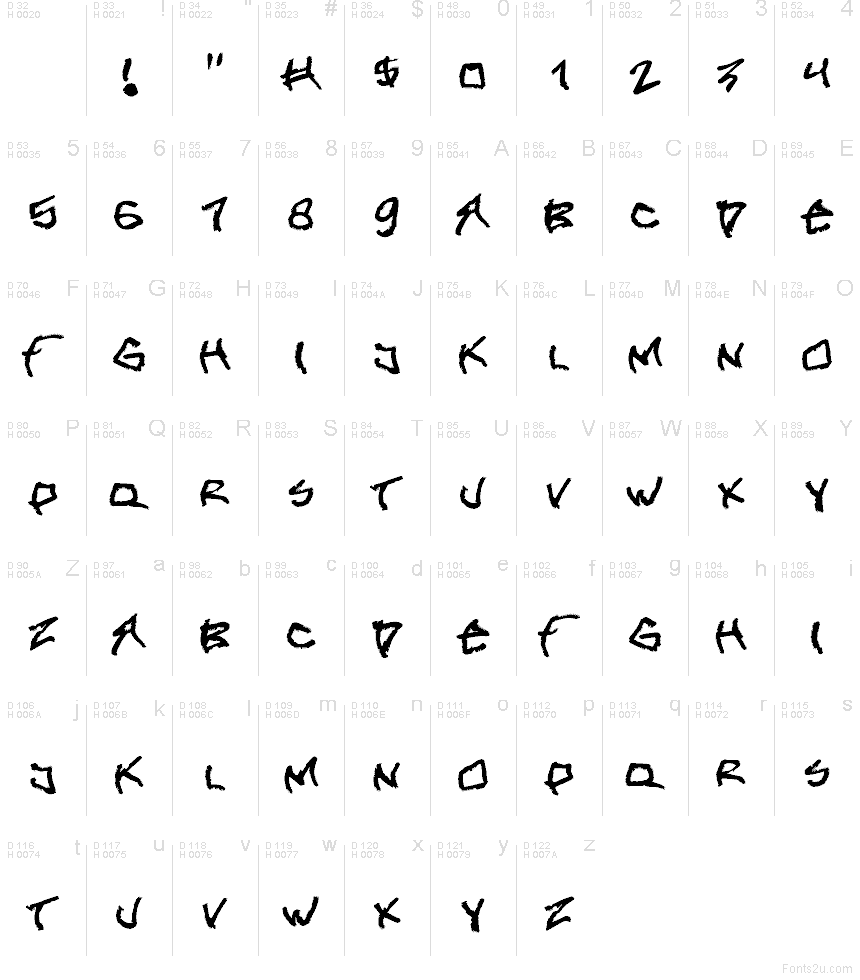
Urban Cile Graffiti autorstwa Ffeeaarr to darmowy krój pisma typu pędzelkowe graffiti z mocnymi, malowanymi ręcznie wielkimi literami. Jego szerokie pociągnięcia pędzla przechodzą w postrzępione krawędzie i szorstkie ślady suchego pędzla. Ostre zakręty nadają literom widocznie niespokojny charakter.
Marki streetwearowe i związane z rozrywką młodzieżową mogą wykorzystać jego surowy, malowany wygląd do projektowania logo, gadżetów i plakatów wydarzeń, gdzie litery stają się częścią dzieła sztuki, a nie neutralnym pismem. Ten krój sprawdza się również w przypadku wydawnictw muzycznych i grafik deskorolkowych skierowanych do odbiorców ceniących kulturę DIY i sztukę miejską.